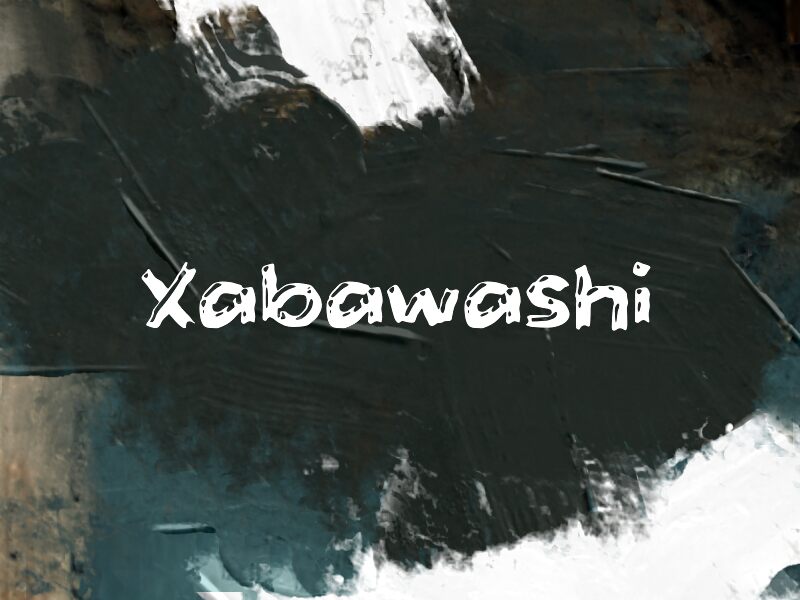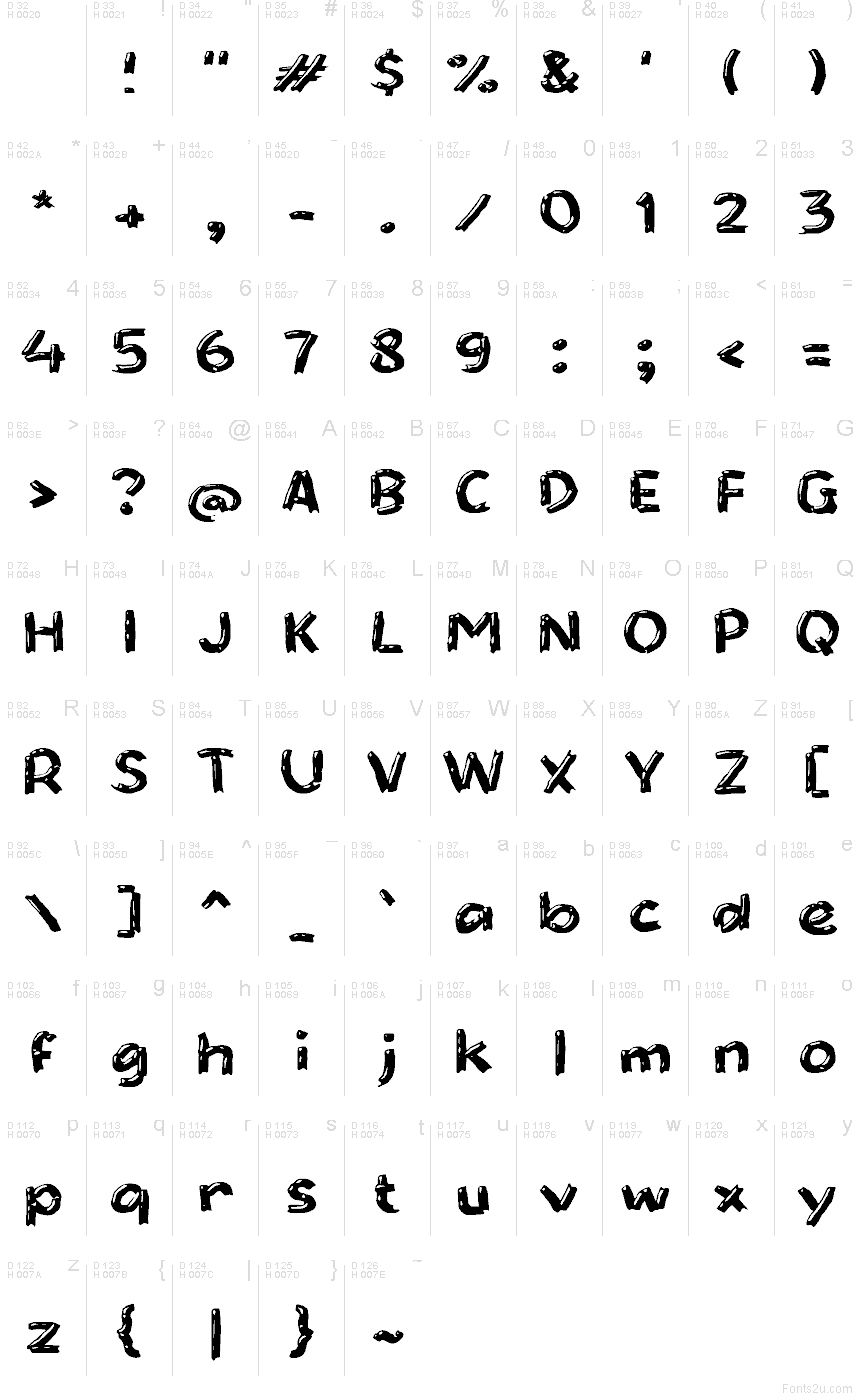
Xabawashi od Wep to darmowy, pełen wigoru krój displayowy z ręcznie rysowanym, niemal przesiąkniętym tuszem wyglądem. Litery są miękkie i nieregularne, z wydętymi krzywiznami, zwężanymi łączeniami i drobnymi wycięciami, które sprawiają, że kształty wydają się mokre, puszyste i nieco figlarne.
To sprawia, że jest to naturalny wybór do nagłówków na plakatach, opakowań przekąsek, zabawnego brandingu, tytułów w stylu komiksowym oraz okładek płyt czy zinów, gdzie liternictwo potrzebuje swobodnego, animowanego charakteru. Jako darmowy font, sprawdza się również w krótkich logotypach, grafikach na merch i nagłówkach w mediach społecznościowych, zwłaszcza gdy szukasz grubych liter, które wyglądają, jakby zostały wylane, a nie wykreślone.